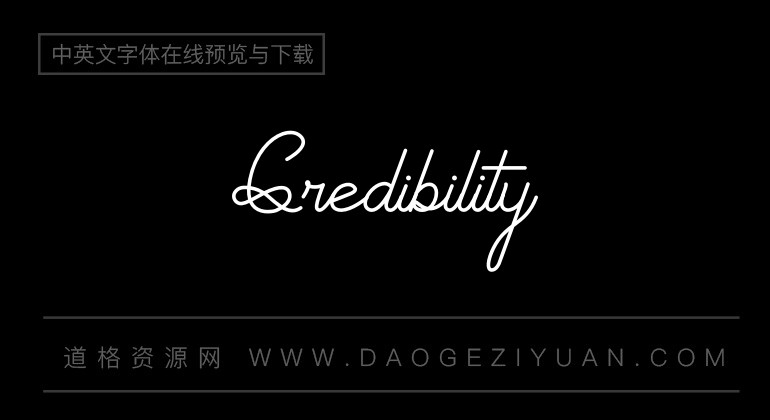
Credibility
Credibility 是一款具有可信度的清晰字体,它结合了现代技术和传统设计,专为大型媒体和企业定制。它具有易读性和视觉冲击力,可以有效地传达消息,使企业形象更加专业。它具有良好的细节和结构,可以提高设计的可读性,使文字更加清晰可见,具有良好的可读性和可视性。
Credibility是一款非常不错的手写艺术字体,具有很好的视觉感,适合于文化类的宣传设计、商业类品牌的广告和产品包装设计以及个性化文字排版等较多场景。